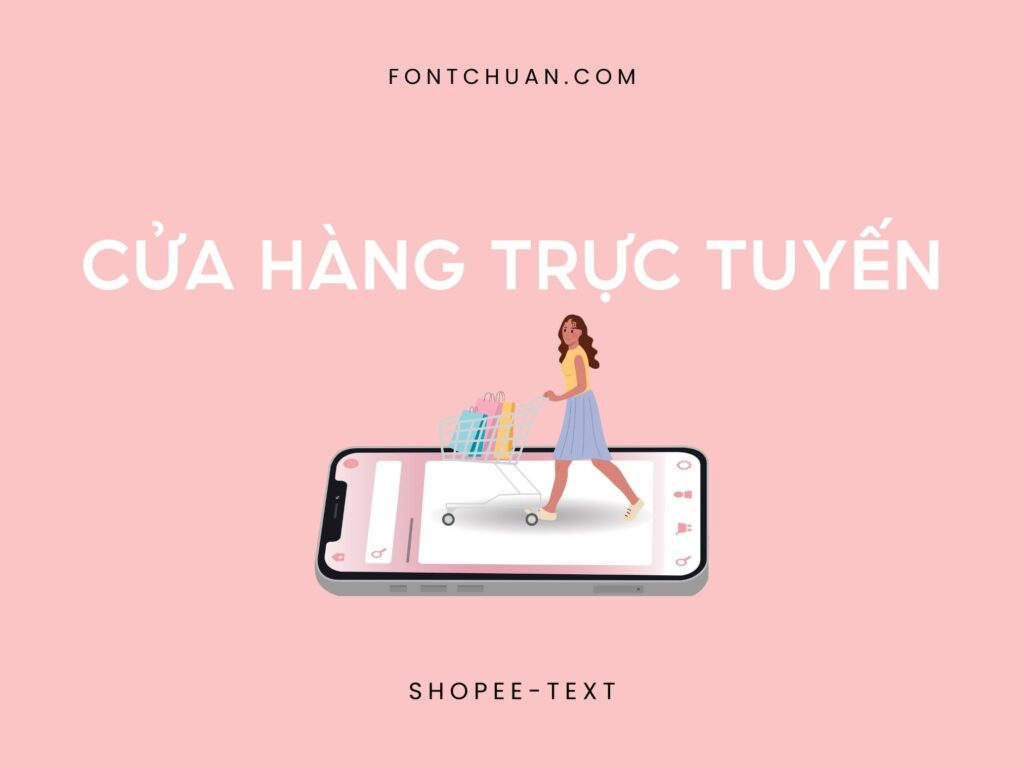
Font Shopee Display & Fvh Shopee Text Việt Hóa
Shopee Display và FVH Shopee Text là bộ font nhận diện thương hiệu chính thức của Shopee, được phát triển bởi đội ngũ thiết kế của Shopee. Bộ font này bao gồm các biến thể như Shopee Display Light, Regular, Bold, ExtraBold, Black và FVH Shopee Text Bold, mang đến sự linh hoạt cho các dự án thiết kế. Font hỗ trợ tiếng Việt và nhiều ngôn ngữ khác, được sưu tầm và đăng bởi thành viên của Font Chuẩn.
Font có thiết kế hiện đại với các nét chữ rõ ràng, độ dày đa dạng và cấu trúc chắc chắn, tạo nên sự chuyên nghiệp và dễ đọc. Shopee Display và FVH Shopee Text phù hợp cho các thiết kế liên quan đến thương hiệu, truyền thông xã hội, tiêu đề và nội dung số. Đồng thời, bộ font này cũng có thể được sử dụng như một Font chữ spa, phù hợp cho các thiết kế menu, ấn phẩm quảng cáo, banner hoặc poster cho các spa, mang lại cảm giác tinh tế, thư giãn và thân thiện với khách hàng.
Ngoài ra, Shopee Display và FVH Shopee Text cũng thích hợp làm Font chữ công nghệ, phù hợp cho các sản phẩm liên quan đến website, ứng dụng, giao diện người dùng và các tài liệu kỹ thuật, mang đến cảm giác hiện đại, chuyên nghiệp và dễ ứng dụng trong các dự án công nghệ.